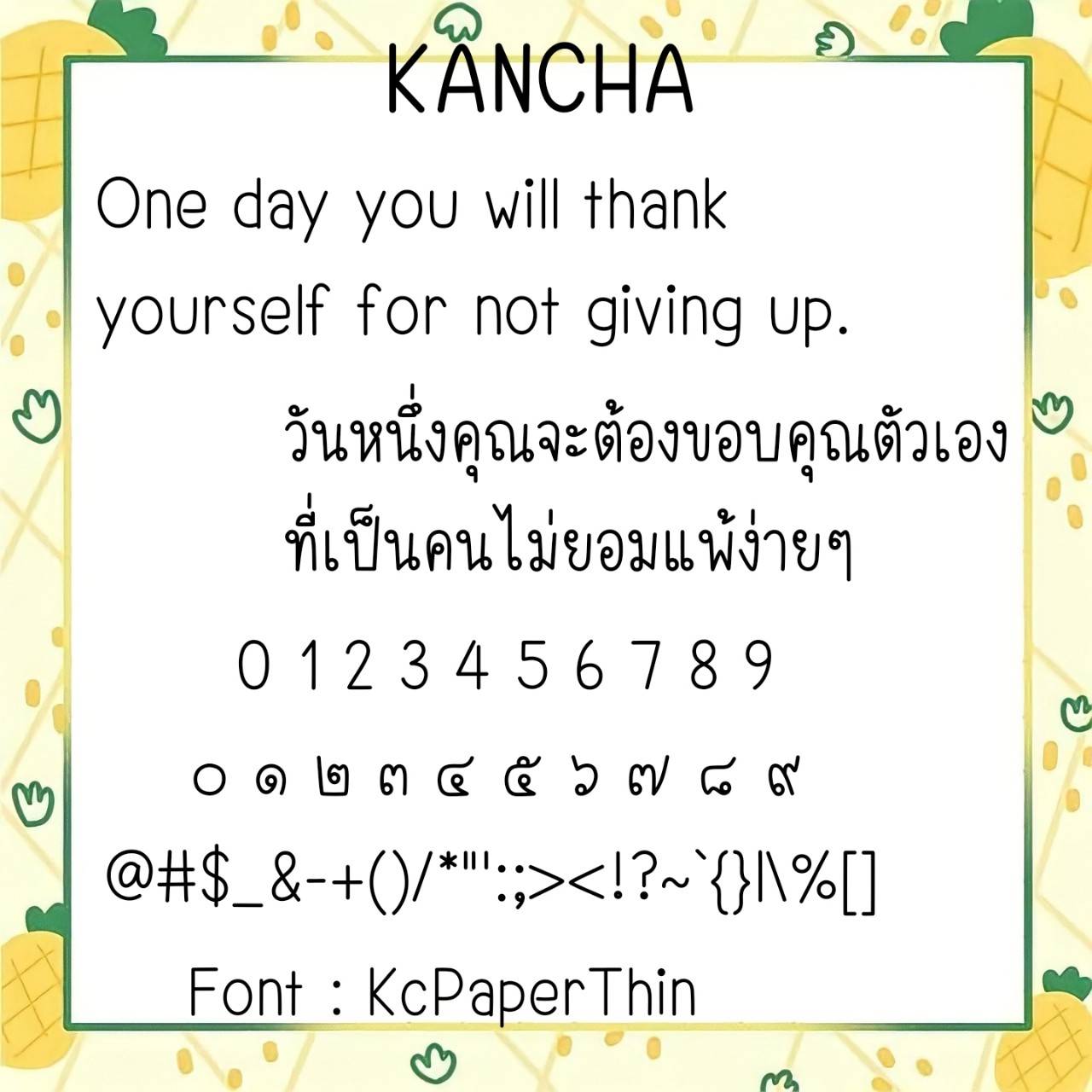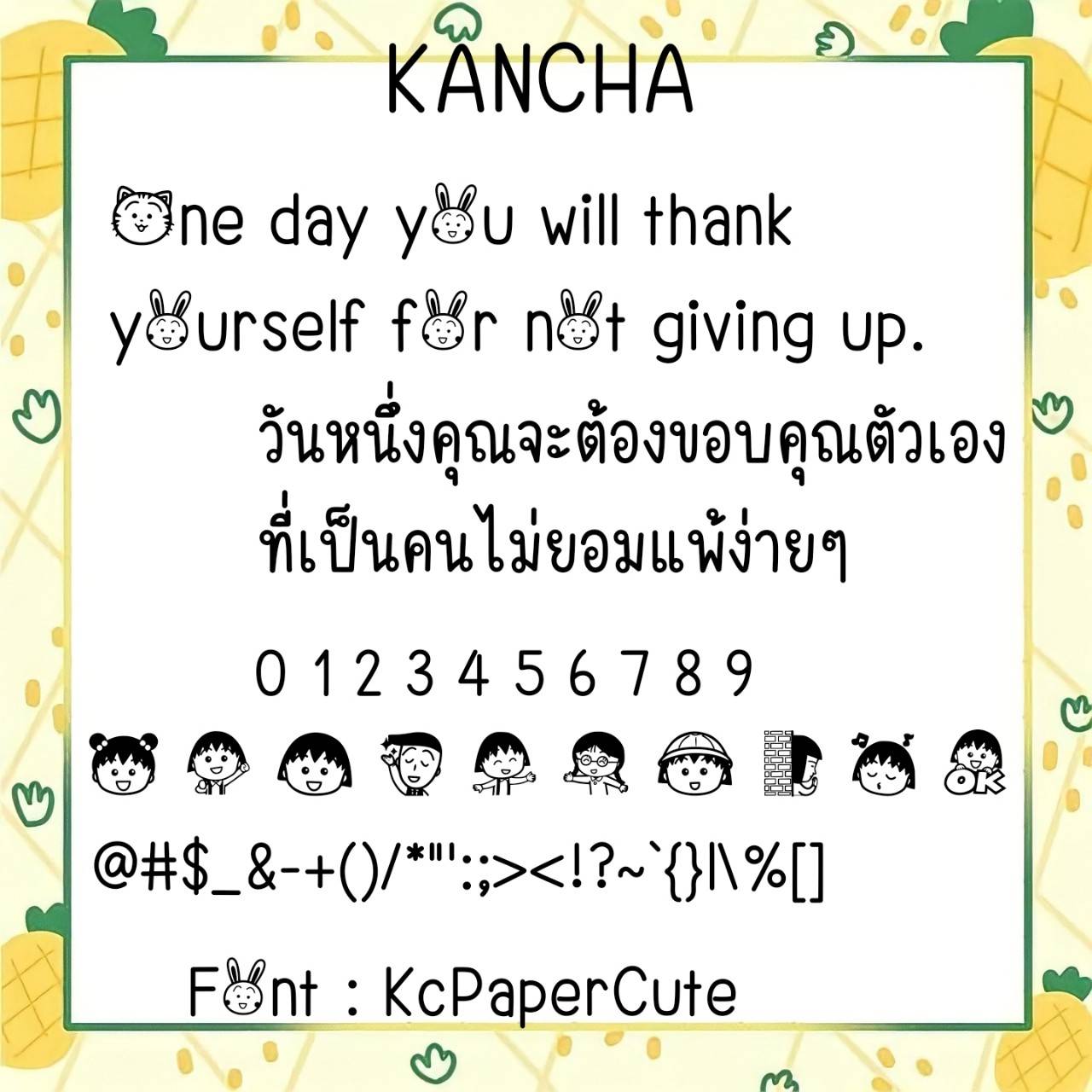
Font KcPaper
ชื่อสินค้า : Font KcPaper 💙
🔸ฟอนต์สไตล์ผอมๆ แต่อ่านง่าย มาพร้อมกับอิโมจิเลขไทยมารูโกะด้วยนะคะ
🔹Slim but easy-to-read style fonts, along with Thai Maruko emojis.🥰💙